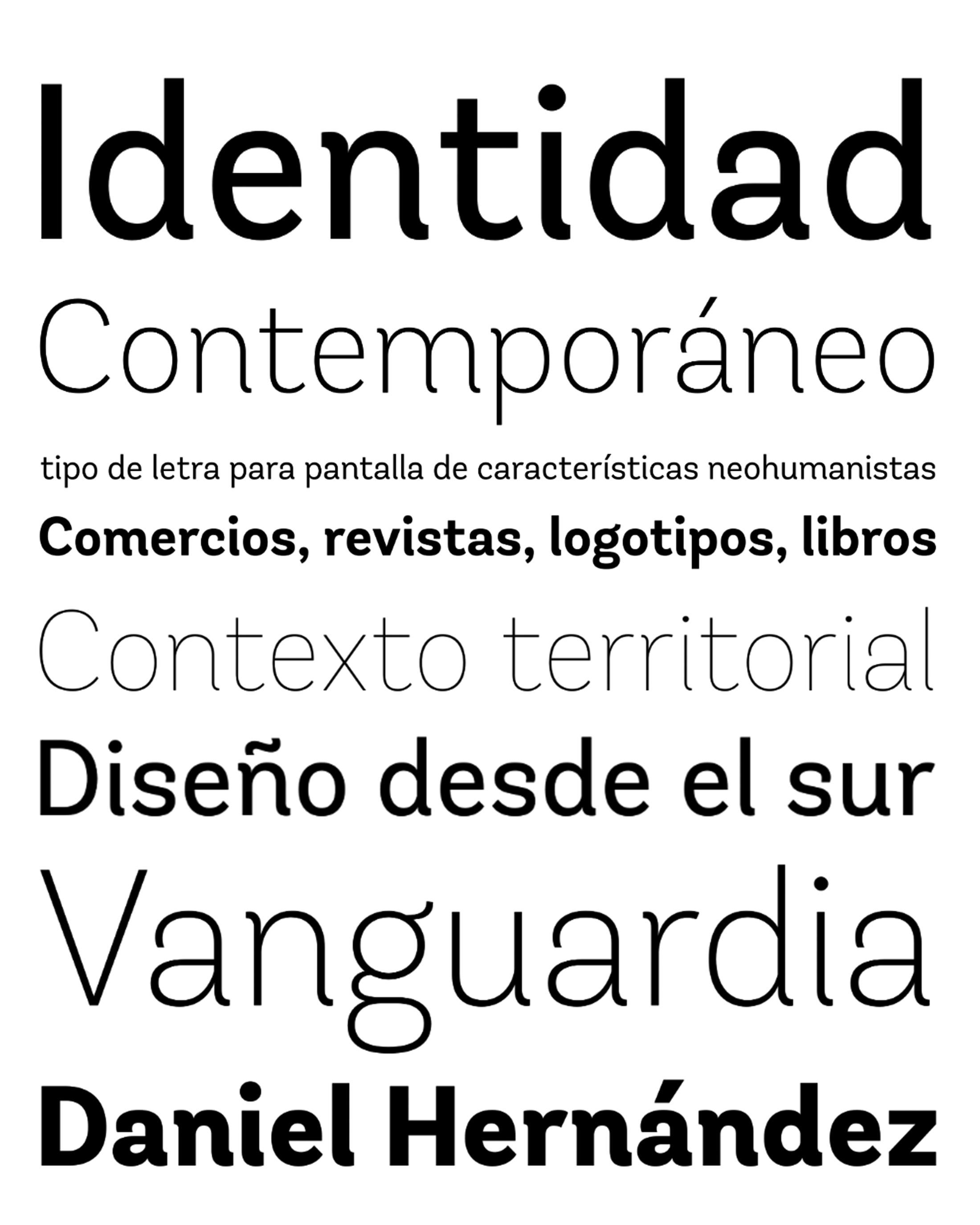
| Año | 2011 |
| Créditos | Daniel Hernández |
| Descripción | Andes, diseñado por Daniel Hernández, es un tipo de letra para pantalla de características neohumanistas. Sus diferentes terminales, entre otros elementos, le dan un aspecto de tipografía mixta. Andes es un tipo de letra con 10 Vertical pesas, 10 Cursiva & Versión resumida. |